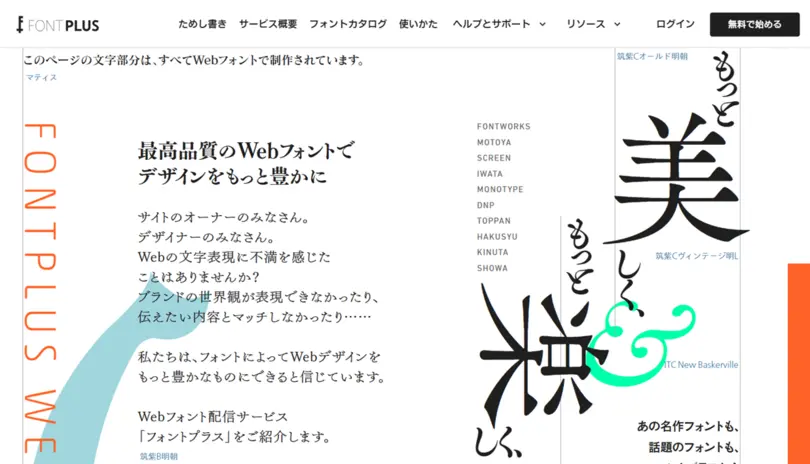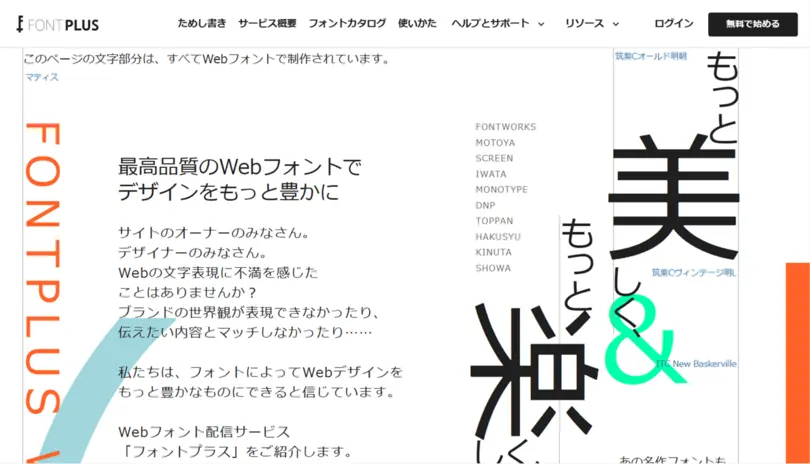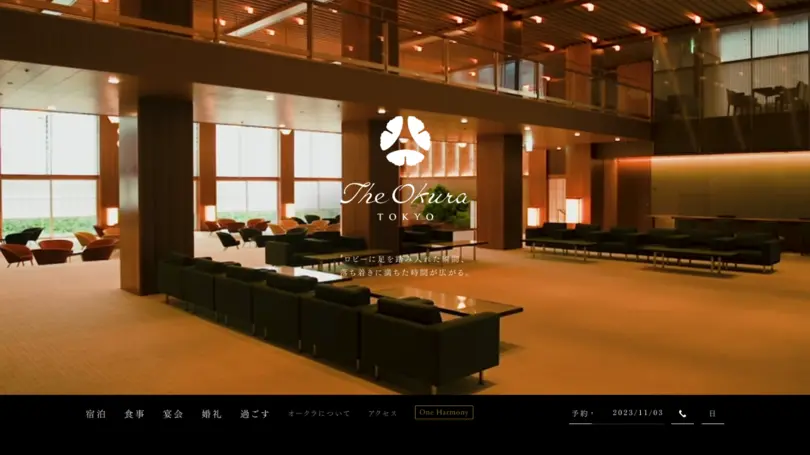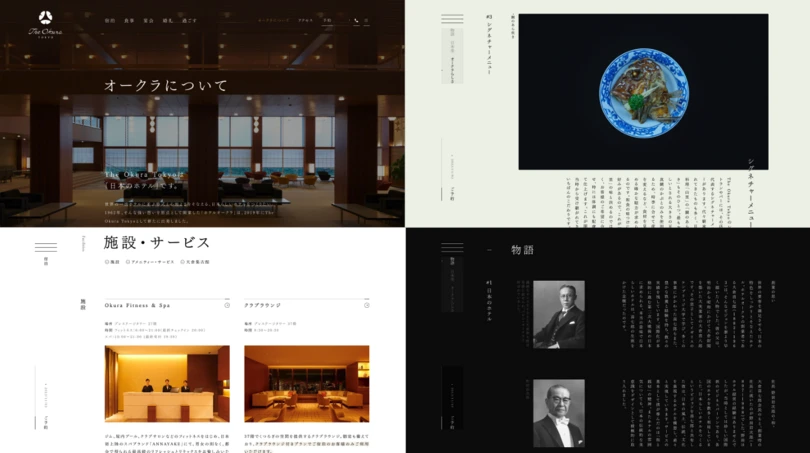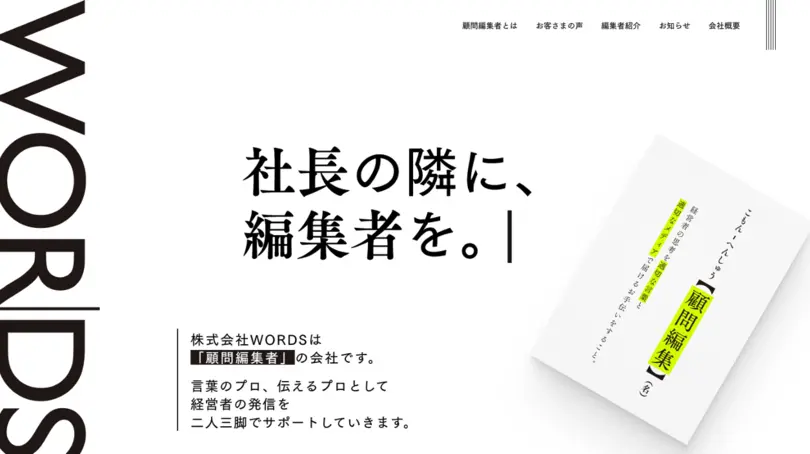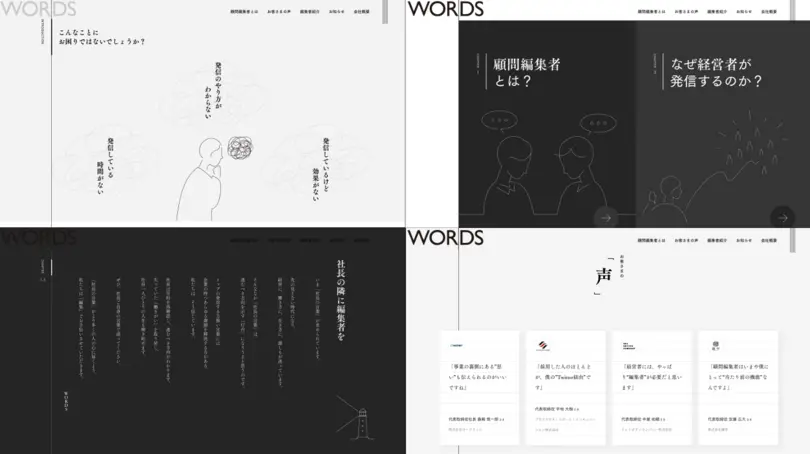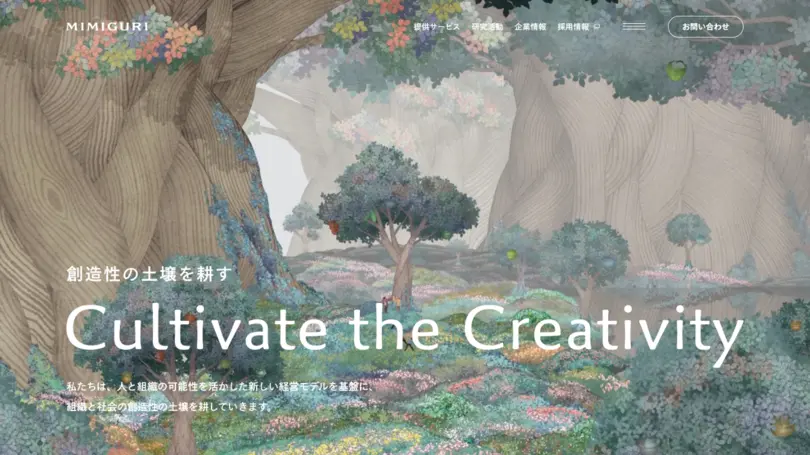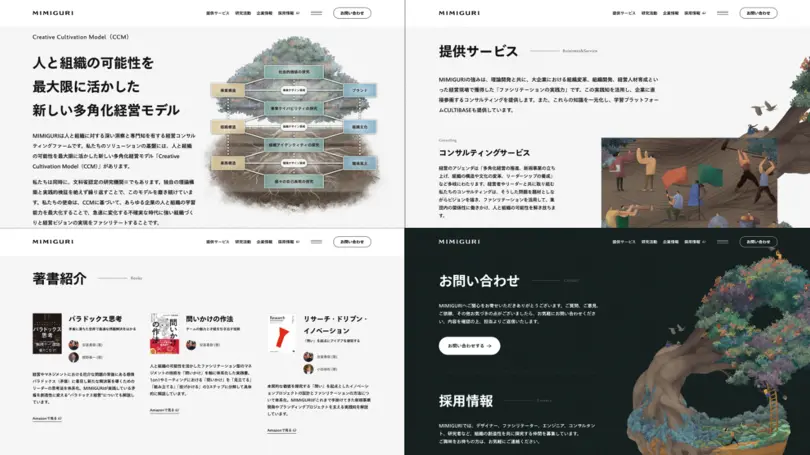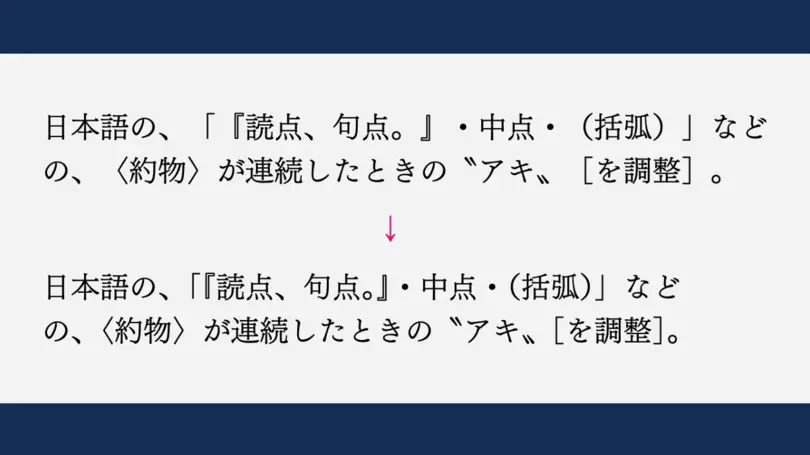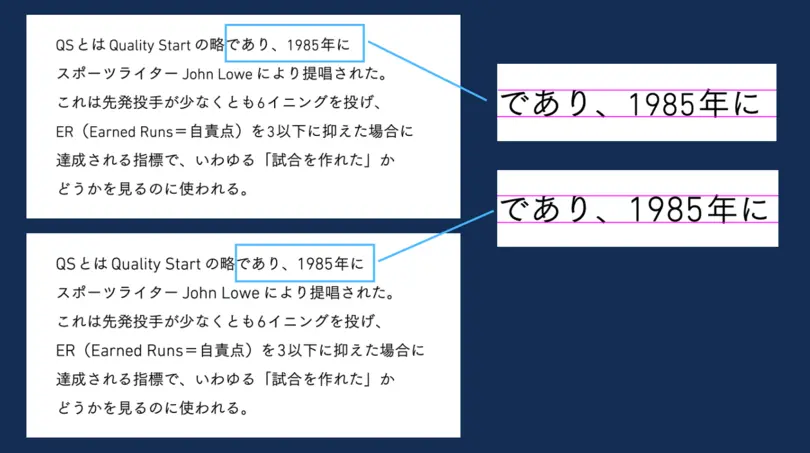
成功に導くブランド創りへ 「Webとタイポグラフィの現在地」
誕生から25年になるWebフォントは、今ではWebデザインになくてはならない存在です。より豊かな表現が可能になったWebタイポグラフィ技術の最新事情について、Webフォント配信サービスFONTPLUSの取り組みを交えながら紹介します。
2023年11月10日にMonotype主催のタイポグラフィイベント「Monotype+(モノタイププラス)」がスパイラルホール(東京・青山)にて開催されました。
過去10回にわたり運営してきたType&(タイプアンド)の名前を改め、再スタートする運びとなったMonotype+は、9月にMonotypeグループの傘下に入ったフォントワークス株式会社(以下フォントワークス)と初めての合同イベントになりました。
第一回となる今回のテーマを「Typography matters.(タイポグラフィの重要性)」として、タイポグラフィとブランドの関わりについて、グローバル企業を成功に導くブランド創りのソリューションを提供します。
Session 2 は、Webフォント配信サービスFONTPLUSの開発を担当しているフォントワークス 鈴木丈によるプレゼンテーション「Webとタイポグラフィの現在地」です。Webとタイポグラフィにおいてどういったことが可能なのか、実例を交えつつお話ししました。
はじめにWebフォントについて説明しました。
[Webフォント?]
Webフォントとは、その名の通り私たちが普段利用しているWebサイトやWebアプリケーションにおいてフォントを利用する技術のことを言います。スマートフォンやパソコンにはフォントがインストールされています。これはシステムフォントとも呼ばれていますが、O Sやデバイス、環境に応じて違うフォントを採用しているため、(Webフォントを利用していない場合)同じWebサイトを表示しても違うフォントで表示されることが多々あります。同じブランドの印象やメッセージを伝えたい場合は、違って見えてしまい、同じユーザー体験を提供側がコントロールできないという課題があります。
そこでWebフォントを採用することにより、環境に左右されずに、統一したユーザー体験を提供することが可能になります。これがWebフォントの基本的な仕組みです。2011年より提供を開始したFONTPLUSでは、現在4,000近い種類のWebフォントを保有しています。
Webフォントのメリットは、システムフォントにはない表現力豊かなフォントが自由に使える点が最大の魅力です。筑紫明朝などのWebフォントと、システムフォントであるメイリオが適用された二つのページを見ると、内容は問題なく読めるがページから受ける印象は全く異なるということがわかると思います。
Webフォントを使用したページ
システムフォントを使用したページ
[読めればいい?]から[読める→伝わる]へ
WindowsのメイリオやmacOSに入っているヒラギノは、汎用的になるべく多くの方に読みやすい可読性の高いものとして選ばれているシステムフォントです。
企業のメッセージやブランドの世界観、または個人の考え方などを伝えたい時によりふさわしいフォントがあるのではないかという考えのもとFONTPLUSチームは日々開発を行っています。
[読める→心地よく読める]
現在、私たちはWeb上で多くの時間を費やすようになりました。これに伴い適切なフォントを選ぶということだけではなく、どのように画面に配置するか、行間や文字のサイズなどタイポグラフィの問題についても非常に重要になります。
後半は、FONTPLUSを導入した企業事例を通してWebフォントの魅力を解説いたしました。
[ブランドの世界観をWebフォントで伝える]
事例1:株式会社ホテルオークラ東京
最初の事例は、株式会社ホテルオークラ東京のWebサイトを紹介。60年代に開業し2019年にリニューアルした日本を代表する一流のホテルになります。
Webサイトのデザインは株式会社マウントが担当しました。このサイトの特徴は、基本的な情報以外に歴史のあるホテルの強みとより良いホスピタリティを提供できる現代的な施設としての魅力を伝えています。ここでは、懐かしさとモダン、しなやかさと緊張感を併せ持つデザインとして筑紫明朝がWebフォントとして採用されました。
このサイトの素晴らしい点は、予約やサイトを訪れる段階でも特別な体験ができるよう、隅々まで設計された筑紫明朝を使ったサイトのタイポグラフィにあります。Webサイトを通して企業の姿勢やメッセージを存分に堪能できるブランドの成功例だと話しました。
事例2:株式会社WORDS(以下Words)
Wordsは、顧問編集者という珍しい業態の会社になります。編集者が言葉のプロとして経営者の発言、発信をサポートし、言葉によって企業をブランディングしていくというミッションを持っています。Webサイトも言葉が主役となったデザインとして株式会社neccoが制作。ここでは筑紫Aオールド明朝と筑紫ゴシックを採用しています。の二つのフォントが巧みに組み合わさり、言葉の力でブランディングをサポートしていくというメッセージがストレートに伝わるデザインになっています。
Webサイトを制作する際、サイトデザインが先に進み、コンテンツはあとから決まって掲載されることもあると思いますが、このサイトはデザインの初期の段階からデザインやレイアウトとコンテンツを同時に考えて進められました。言葉を軸にしてコンテンツとデザインが相互に影響しあいながら生まれたWebサイトになります。さらに、Webからダウンロードする案内資料についても統一したデザインで制作され、常に同じ企業メッセージを発信することができている例です。
事例3:株式会社MIMIGURI(以下Mimiguri)
経営組織、マーケティングデザインなどのコンサルファームであるMimiguriのWebサイトの紹介です。採用されているWebフォントはMonotypeのたづがね角ゴシックです。文部科学省認定の研究機関であるMimiguriのメンバーの多くは、本を執筆しているという背景もあり、コンテンツはアカデミックな単語が並びます。サイトを訪れたユーザーとの距離感を大切にするためにも、知的で洗練されたイメージを保ちながらも温かみのあるたづがねの強みが生かされています。また、グラフィックと合せることでより柔らかさと親しみやすさを演出することができているサイトであると鈴木は話します。
続いて、Webフォントを効果的に利用できるためのFONTPLUSの機能を紹介しました。
[タイポグラフィ タイプ(活字、フォント)をいかに配置するか]
FONTPLUSでは、Webフォントに機能を搭載すれば、ブラウザ上で日本語の読点、句点、中点、括弧などの役物が連続した時のアキを自動で調整できるようになっています。
和欧混植する際は、和文の中の英数字だけ小さく見えるという問題がありましたが、Webフォントの技術を使ってより簡単に調整することができるようになりました。
これまで、ウェイトやスタイルはそれぞれ違ったフォントファイルとして扱うことが必要でしたが、この複数のバリエーションを1つのフォントファイルとして利用することができるバリアブルフォントの登場により、これまでの表現の幅を広げることを可能にしました。高度なタイポグラフィ表現にはブラウザー側の技術とフォントの機能というものが必須ですが、ここ数年の急激な進化によりこれまでできなかったことが次々とできるようになってきました。
最後に現在のWebデザインとフォントワークスの取り組みを紹介しました。
[Webデザインを取り巻く環境の変化とフォントワークの取り組み]
コラボレーション
これまではデザイナーが1人で最初から最後まで行っていましたが、現在ではFigma、XDなどのコラボレーションツールを使ってチームと連携しながら進めるということが主流になってきています。エンジニアリングだと、GitHubを使用しレビューをしあいながら開発することが当たり前になりました。また、Wixなどのツールを使えば、ソースコードを書かずにホームページを作成するための必要な全ての機能とソリューションを利用することができます。
パフォーマンス
近年、JavaScriptを中心としたフロントエンド技術が飛躍的な進歩を遂げています。これにより画面上で表示速度が早く、より軽快に動くWebサイトやWebアプリケーションが求められています。
フォントワークスでは、FONTPLUSアドバンスト・プランとしてこの新しいニーズにも対応できるようなサービスの開発を進めています。このソリューションは、高速で安定した配信とシンプルで簡単な導入方法を可能にしたものです。
FONTPLUSチームでは、今後もWebの領域においてTypography matters.(タイポグラフィの重要性)をより多くの方に理解してもらえるような活動を進めていきます。